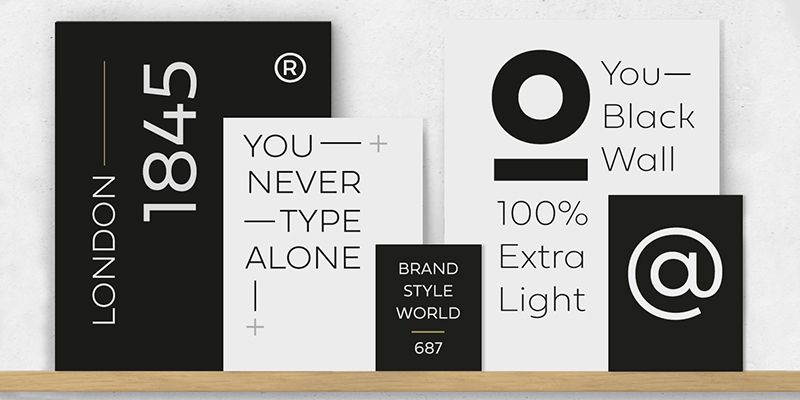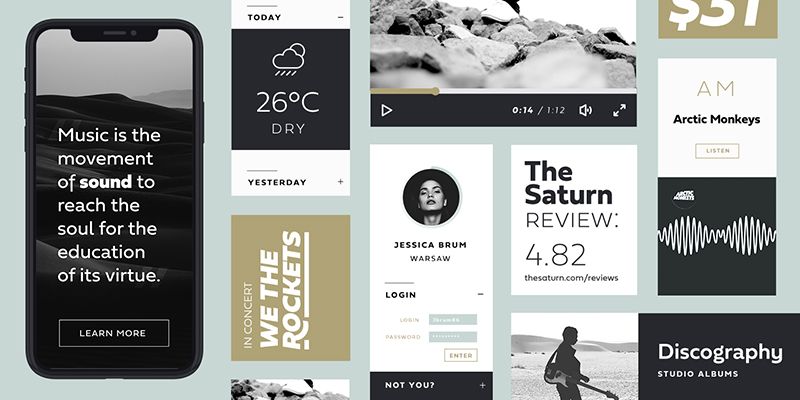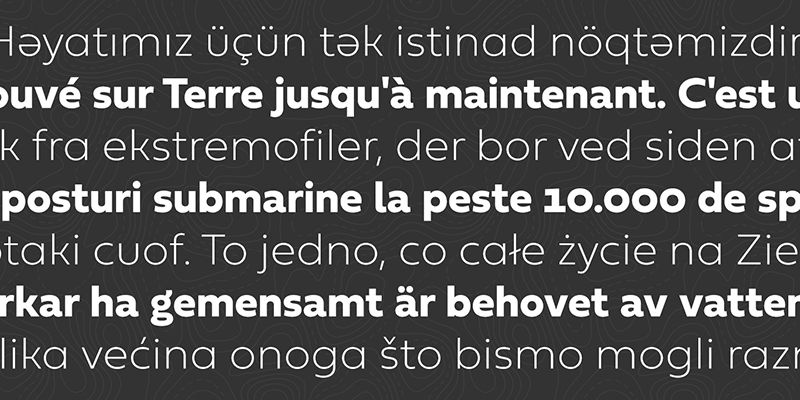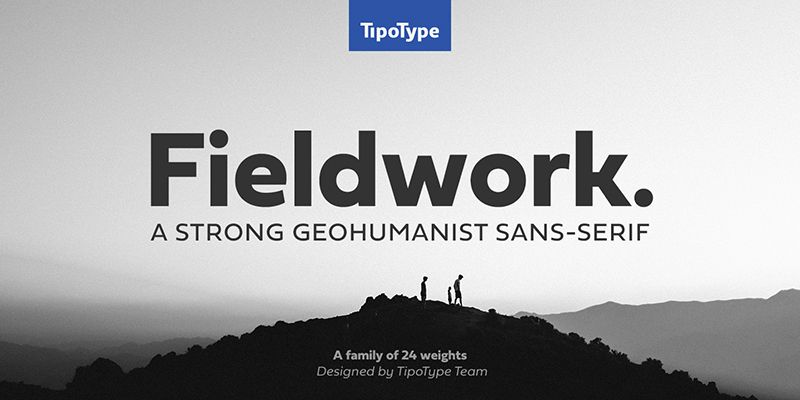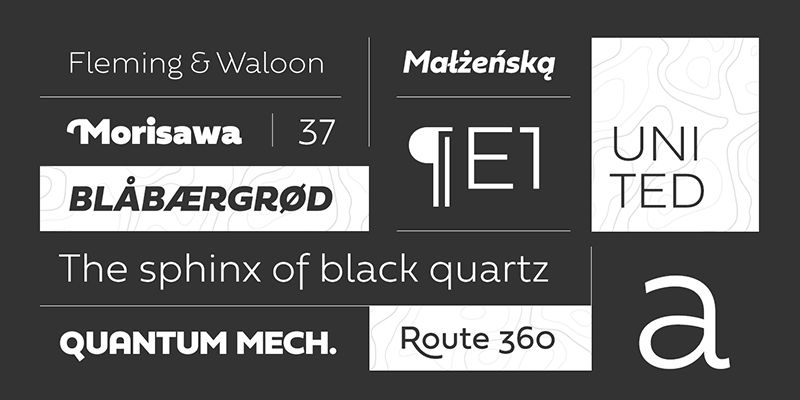
Fieldwork의 모양은 모든 두께 설정에 대한 대체 문자, 스와시 및 이탤릭체로 성장하는 하나의 시스템에서 기하학적 획(Geo)과 2단 글리프(Hum)의 인간적인 따뜻함을 성공적으로 결합하고 있습니다.
OpenType을 사용하면 작은 대문자, 대체 문자, 스타일 세트 등과 같은 당사 제품의 모든 전문적인 기능을 활용할 수 있습니다.